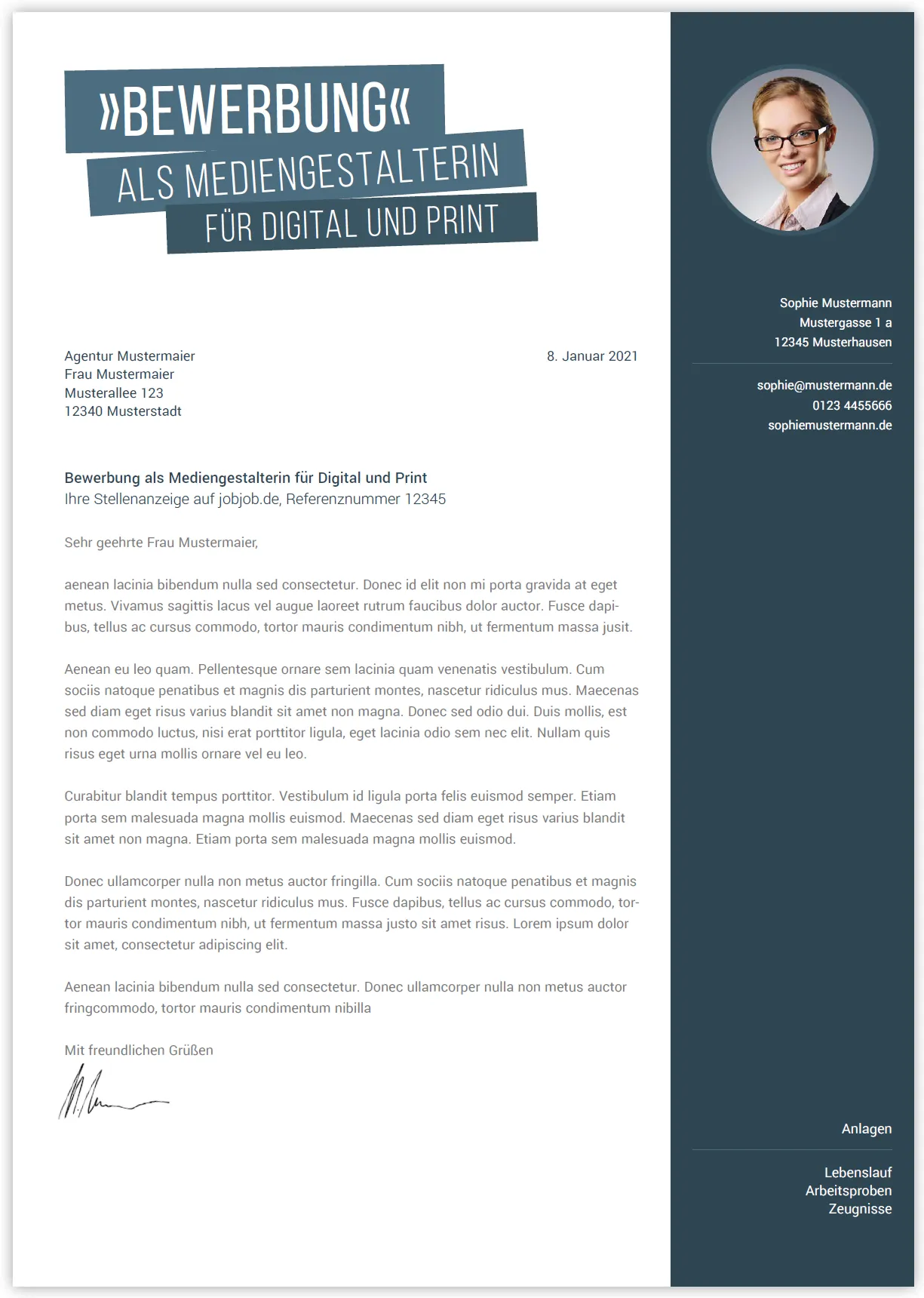
Bewerbung: Schriftarten, Schriftgröße & 12 Tipps zu Vorgehen und Gestaltung
Welche Schriftarten empfehlen sich für eine Bewerbung? In welcher Schriftgröße solltest du sie verwenden? Zu Schriftart und Textgröße in Bewerbungen gibt es hier ausführliche Hinweise. Zunächst starten wir mit 12 Tipps rund um dein Vorgehen beim Erstellen deiner Bewerbung und zur Gestaltung deiner Unterlagen.
Bewerbung: Schriftarten, Schriftgröße & 12 Tipps zu Vorgehen und Gestaltung
1 | Umfang und Seitenformat einer Bewerbung
Egal, wie viel du gern schreiben würdest: In der Kürze liegt tatsächlich die Würze! Dein Schreiben sollte zusammen mit allen erforderlichen Randinformationen am Ende auf eine DIN-A4-Seite passen. Deren Maße liegen bei 21 cm × 29,7 cm. Klassischerweise stellst du den linken Seitenrand auf 2,5 cm, alle anderen (oben, unten und rechts) auf 2 cm. Doch Vorsicht: Der Text deines Bewerbungsschreibens selbst sollte sich nicht über die gesamte Seitenbreite erstrecken. Eine Zeilenlänge von circa 60 bis 70 Zeichen bietet hingegen einen hohen Lesekomfort.
Bewerbung: Schriftarten, Schriftgröße
2 | Kopfzeile
Deine Kontaktdaten kannst du ganz wunderbar auch in der Kopfzeile unterbringen. Verwende zum Beispiel eine zweizeilige Darstellung: In der ersten Zeile platzierst du deinen Namen in größerer Schrift (15 oder 16 Punkt). Darunter gibst du in der zweiten Zeile in kleinerer Schrift (13 oder 14 Punkt) deine Daten an, die du zum Beispiel durch einen Trennstrich (|) oder einen Mittelpunkt (•) voneinander trennst. Ist dein Bewerbungslayout etwas individueller, gelten die Größenvorschläge nicht. Dann achte einfach auf die Struktur, dass der Name fett ist oder größer ist als deine zugehörigen Daten.
3 | Rechter Seitenrand
Auch hier kannst du deine Kontaktdaten unterbringen und eventuell sogar dein Bewerbungsfoto setzen. Solltest du dich für die Variante entscheiden, lässt du für den Seitenrand mehr Platz, wobei sich ungefähr 6 cm eignen. Gleichfalls bietet dir der Seitenrand die Möglichkeit, dein Anlagenverzeichnis unterzubringen. Den Seitenrand kannst du durch eine Trennlinie oder auch durch eine farbige Fläche vom Rest des Schreibens abheben.
Bewerbung:12 Tipps zu Vorgehen und Gestaltung
Ein Beispiel für einen Seitenrand in deiner Bewerbung
4 | Farbe
Alles nur Schwarz auf Weiß? – Das muss nicht sein. Oder anders formuliert: Setze mithilfe deines Designs farbige Akzente, um aus dem Einheitsbrei herauszustechen! Du kannst auch mit sanften Farbabstufungen arbeiten und für verschiedene Designelemente beispielsweise ein helles und ein dunkleres Blau verwenden. Bei der Wahl der Farbe könntest du folgende Überlegungen anstellen:
• Nimm einfach deine Lieblingsfarbe, womit du deine Persönlichkeit mehr in den Fokus rückst.
• Wähle eine Farbe, die der Farbe des Unternehmens entspricht oder nahekommt, bei dem du dich bewirbst.
• Wähle eine Farbe, die für die entsprechende Branche typisch ist. So darf es im Bereich Ökologie gern ein Grün sein.
5 | Konzept
Das Schreiben einer Bewerbung zählt nicht unbedingt zu den Lieblingsaufgaben. Schnell möchte man fertig sein und sich schöneren Dingen widmen. Das beste Mittel für ein effizientes Ergebnis mag da das schnelle Losschreiben sein. Doch Stopp! Mit diesem Vorgehen wirst du am Ende mehr Zeit benötigen, als wenn du dich vorher hinsetzt und ein kleines Konzept erstellst.
Schreibe dir ruhig noch einmal raus, welche Anforderungen in der Ausschreibung gestellt werden. Überlege dir, welche davon eventuell besonders und welche weniger wichtig sind. Gleiche diese Liste mit deinem eigenen Profil ab: Wo kannst du konkret etwas benennen, wo eher weniger? Strukturiere dann dein Schreiben vor. Was soll in die Einleitung? Was in den Hauptteil? Welche Dinge möchtest du am Schluss erwähnen?
Basierend auf dieser groben Skizze wagst du dich schließlich an den Text. Und hier gilt: Nur weil du ein offizielles Schreiben aufsetzt, muss der Ausdruck nicht überbordend formell und gestelzt daherkommen. Verzichte auf Umgangssprache, aber erstelle keinen Gesetzestext. Formuliere kurze Sätze, in denen du sagst, was ist.
Schreiben einer Bewerbung
6 | Kenne deine Zielgruppe
Jeder Text richtet sich an eine ganz bestimmte Zielgruppe – so auch dein Bewerbungsschreiben. Das Schöne dabei: Die Zielgruppe ist hier ziemlich genau definiert. Behalte also bei jedem Satz im Hinterkopf, dass du ihn an die entsprechende Ansprechperson, einen Vorgesetzten oder Personalverantwortlichen richtest. Im Grunde musst du dann nur noch eine Frage beantworten: Was muss diese Person von dir wissen, damit sie überzeugt ist, dass du ihr beziehungsweise dem Unternehmen von Nutzen bist?
7 | Arbeite reduziert
Personalverantwortliche haben sicherlich keine Zeit und Lust, in deinem Bewerbungsschreiben sechs oder mehr Absätze zu lesen. Texte daher so prägnant wie möglich, frei nach dem Motto des französischen Schriftstellers Antoine de Saint-Exupéry: „Perfektion ist nicht dann erreicht, wenn es nichts mehr hinzuzufügen gibt, sondern wenn man nichts mehr weglassen kann.“
Bewerbung Schriftart und Größe
8 | Gescannte Dokumente als Anhang